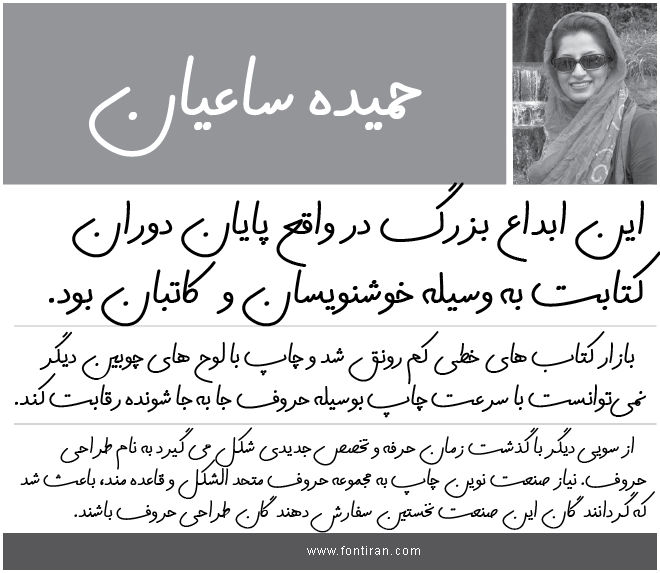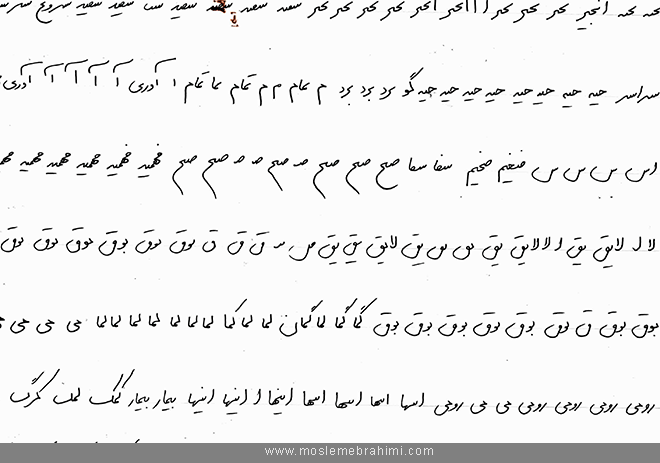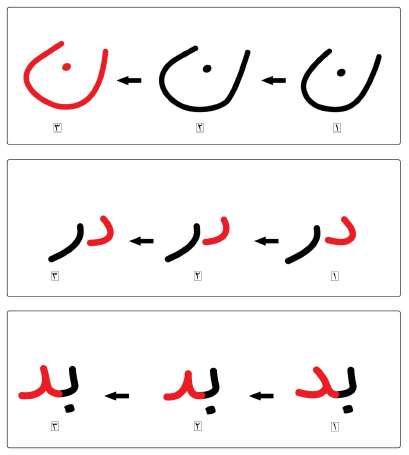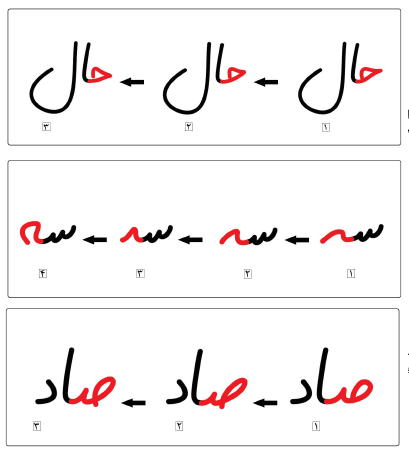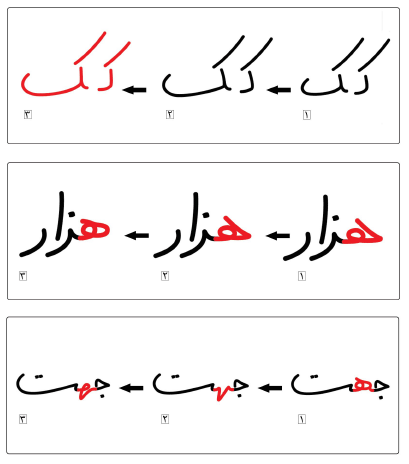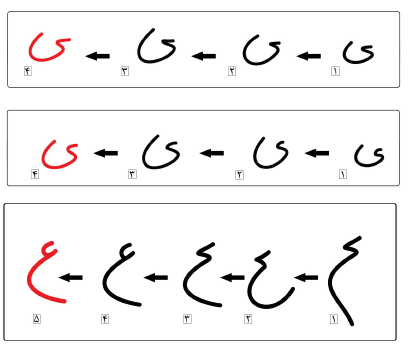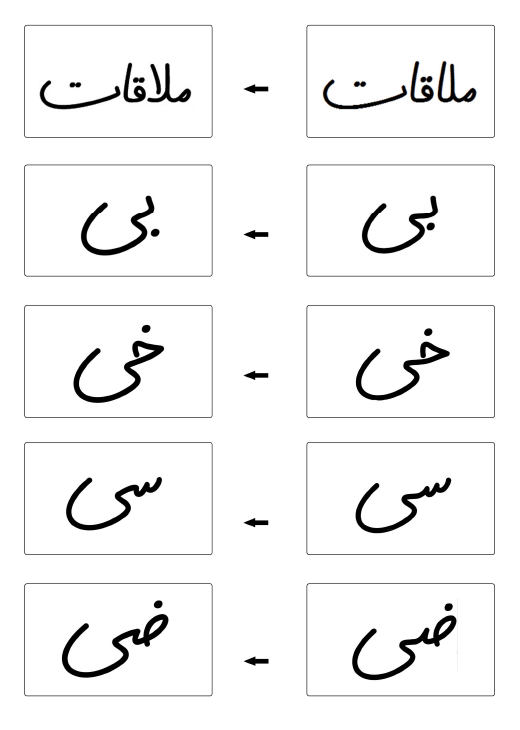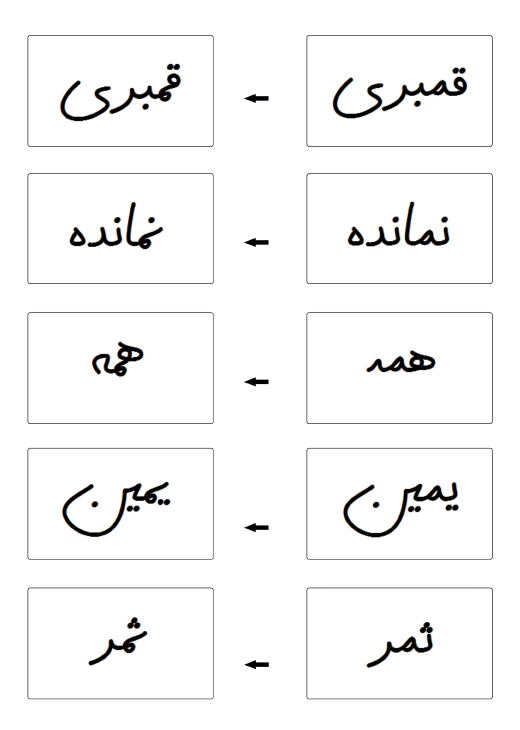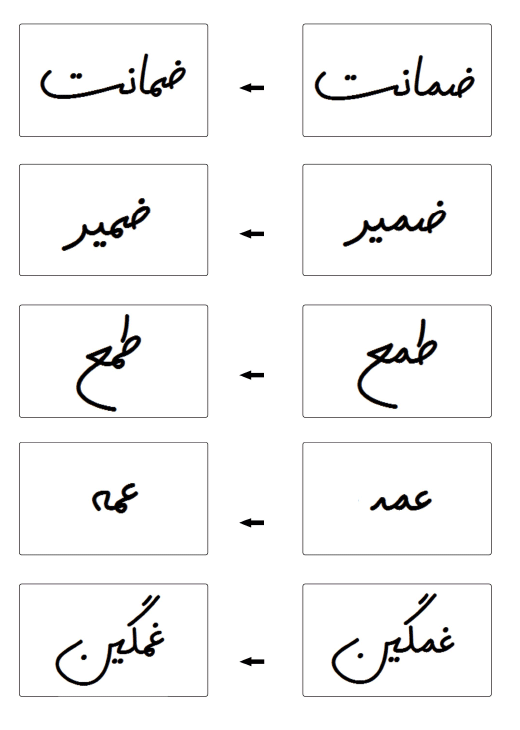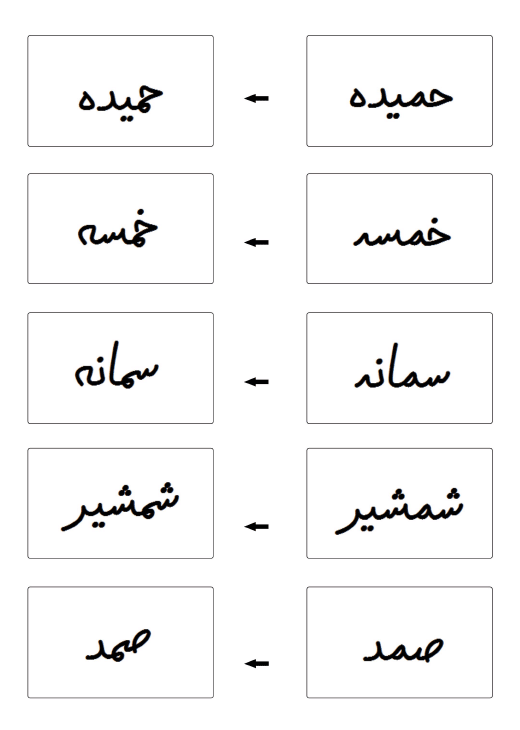
حمیده ساعیان در این پروژه دست خط شخصی خود را به فونت تبدیل کرده است. تبدیل یک دست خط به فونت دارای ظرافت ها و مراحل پیچیده ای است که شرح آن در این قسمت ممکن نیست. اما تصویرهایی از مراحل کار را در ادامه خواهید دید که برخی از مراحل کار را نشان می دهد.
تصویر زیرنشان میدهد که اگرچه طراح به دست خط خود مسلط است اما نیاز دارد بررسی تحلیلی و تمرین های خوشنویسانه داشته باشد تا مناسب ترین شکل حروف را نگارش کند.
در نمودارهای زیر طراح به خوبی تلاش های خود را برای دستیابی به بهترین فرم حروف نشان داه است.
این فونت دست نویس دارای ترکیبات زیادی است که با حوصله و دقت به فونت اضافه شده است. تعدادی از این ترکیبات را می توانید با کلیک بر تصاویر زیر ببینید.
(البته اغلب نرم افزار های حروفچینی امکان صرف نظر کردن از این ترکیبات را هم به شما می دهند)